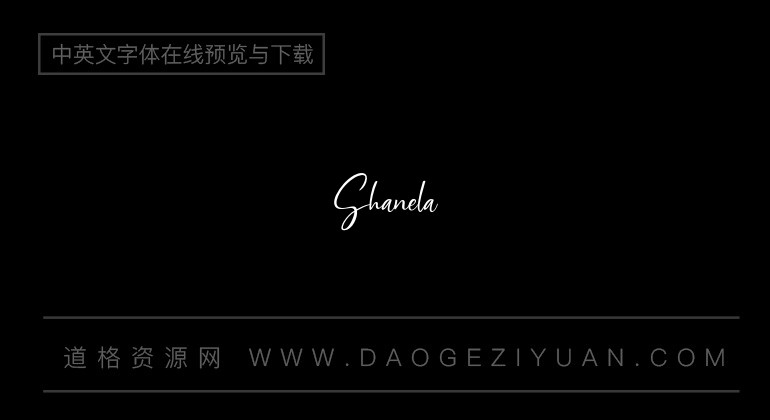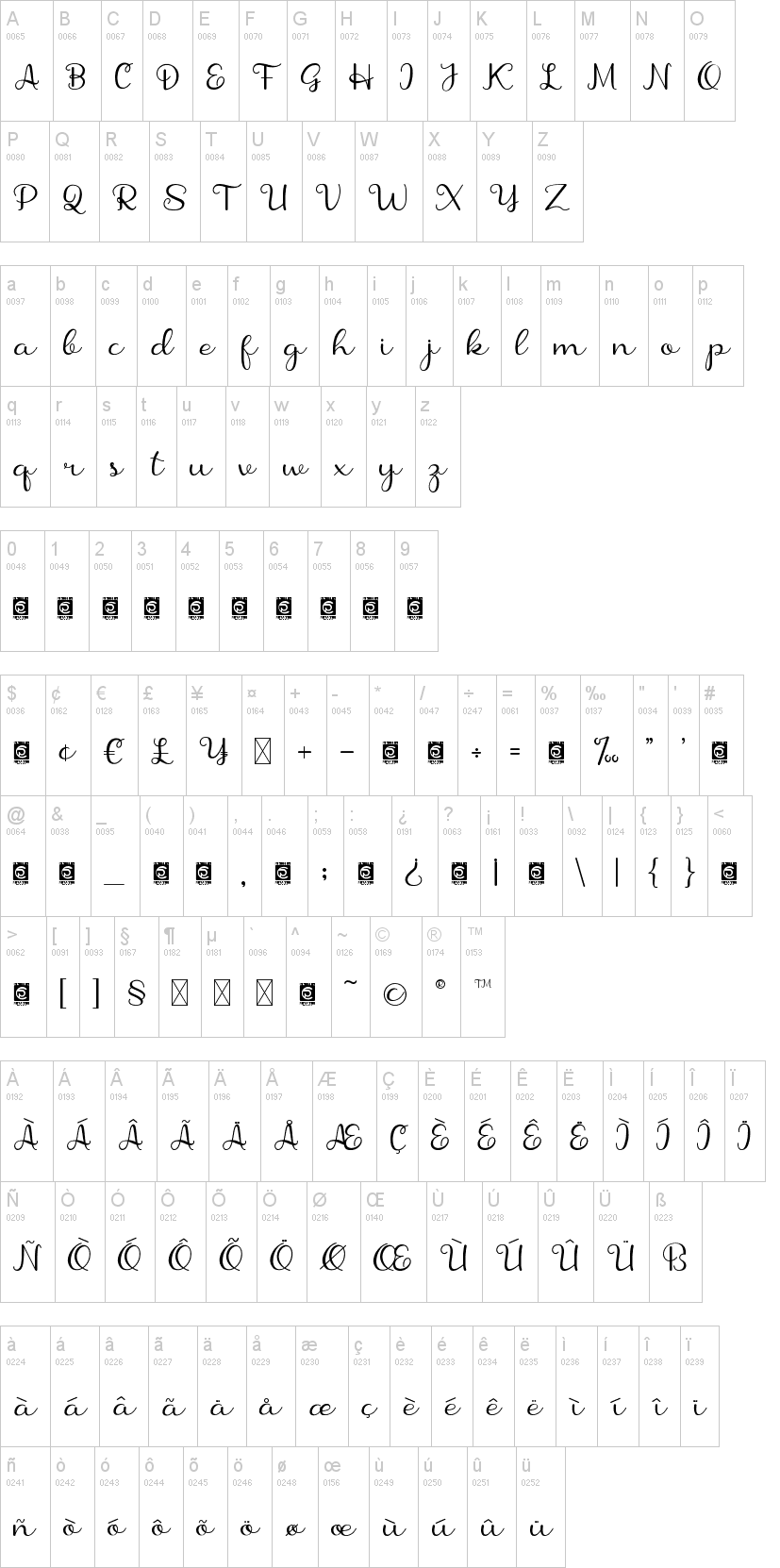
? Shanela 字体是一款简洁、明快的英文字体,它的字体风格类似于英文手写体,但更加细腻,更具有个性。Shanela 字体的特点是文字的笔画清晰,线条流畅,字体整体给人一种清新、活泼的感觉,适合用于报纸、杂志、海报等设计中。内容介绍
Shanela是一款非常不错的手写艺术字体,具有很好的视觉感,适合于文化类的宣传设计、商业类品牌的广告和产品包装设计以及个性化文字排版等较多场景。